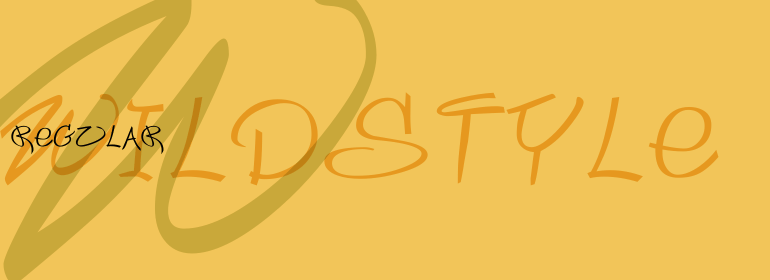
Wildstyle
Wildstyle,这款字体结构工整、笔画清晰,兼顾美观与易读性,适用于标题、正文、海报、包装、LOGO 等多种场景。字形优雅稳定,风格百搭耐看,适配日常排版与创意设计,让文字呈现更舒适、更具质感。Wildstyle一笔一画,皆是细节,以均衡的比例、流畅的线条打造舒适视觉体验,字形端正大气,风格简约现代。无论是商业设计、品牌宣传还是日常排版,都能轻松驾驭,让文字更有格调与力量。Wildstyle字体下载。